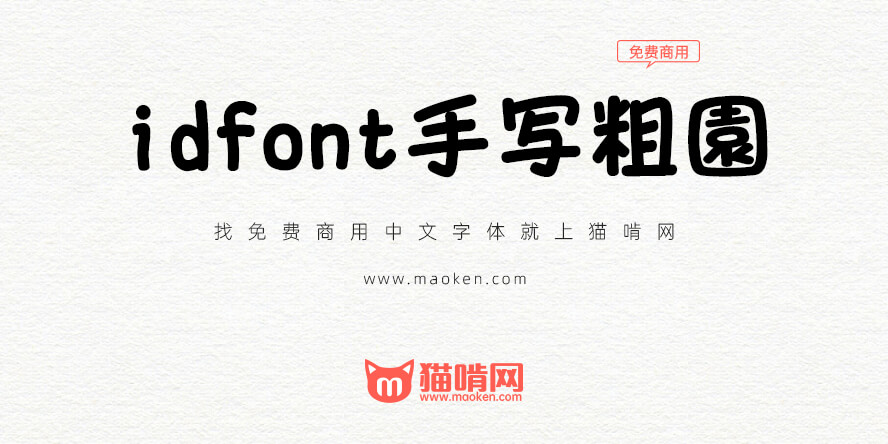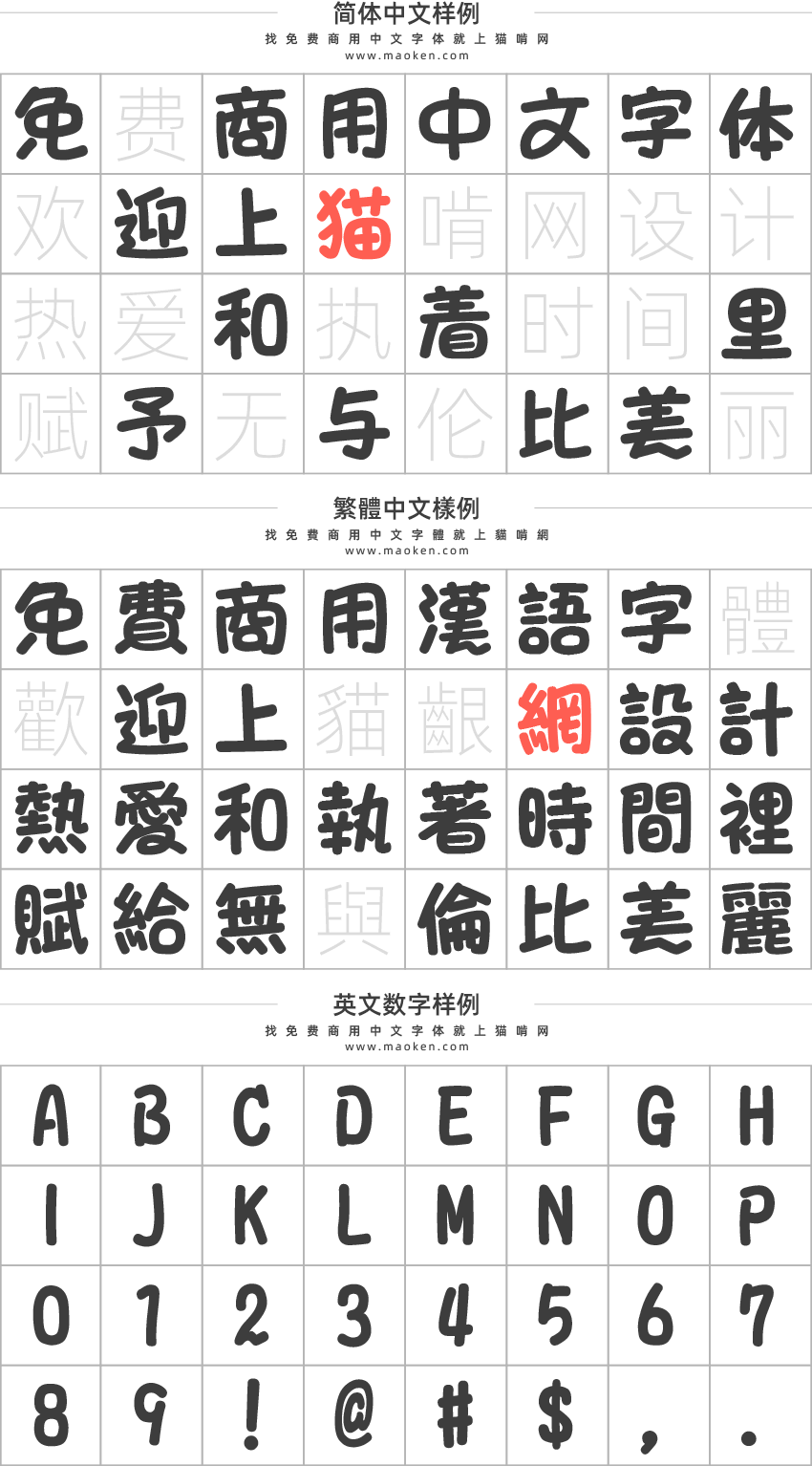
idfont手写粗圆:井上デザイン出品日系POP手写海报字体 免费商用
字体作者:井上デザイン (其他语种) 字体字重:2个
idfont手写粗圆(日文名:あいでぃーぽっぷふとまる)是日本设计师@井上デザイン出品的一款POP日系POP手写海报字体。这款字体字形十分漂亮,特别适合用于一些促销类海报场景。
根据字数软件统计这款字体包含简体中文字体4402个,其中常用字2470个,但是猫啃君发现其中不少字空白符号来占位的,所以实际上这款字体的字数并不多,连繁体也不算多。并且这款字体不允许嵌入软件分发,也不允许增补修改,十分可惜。大陆的小伙伴们用这款字体的话,就比较尴尬了。
主席,这个字体有一个“细粗”版本和另外两个日本汉字字体,所有者没有上传,但原作者上传了。
这字体很美,但没有特别多的汉子